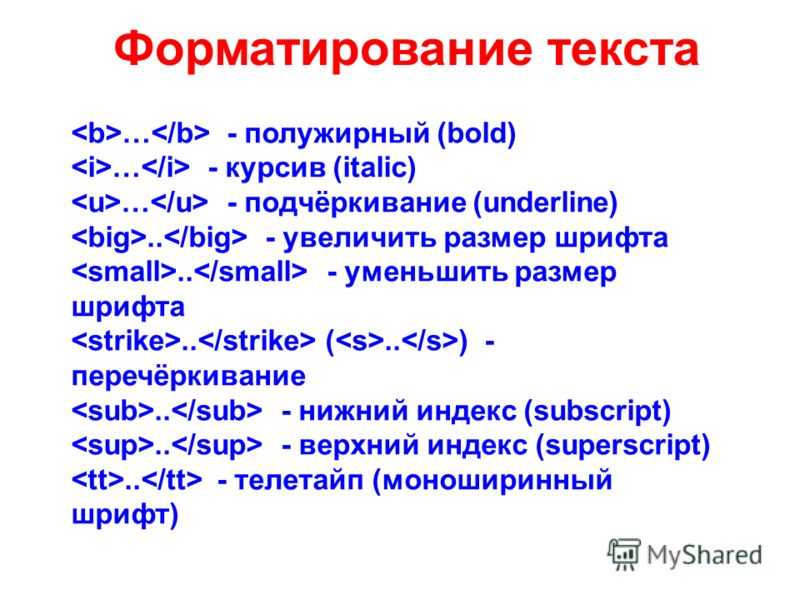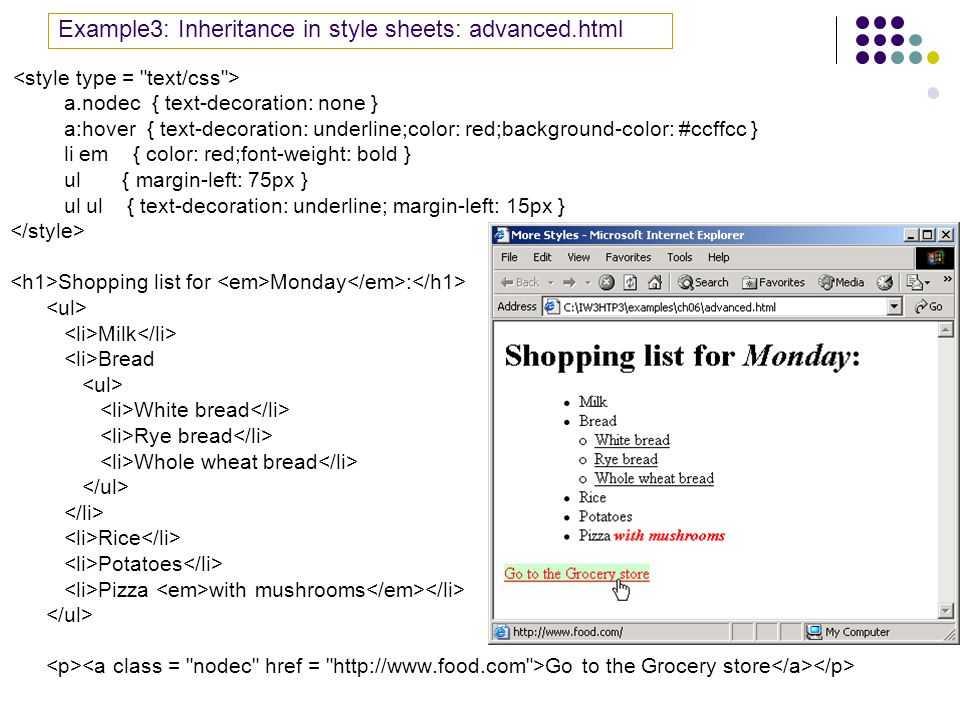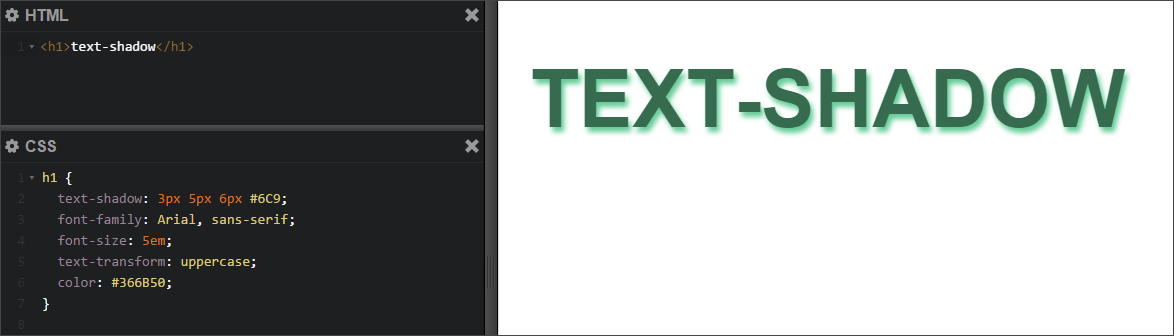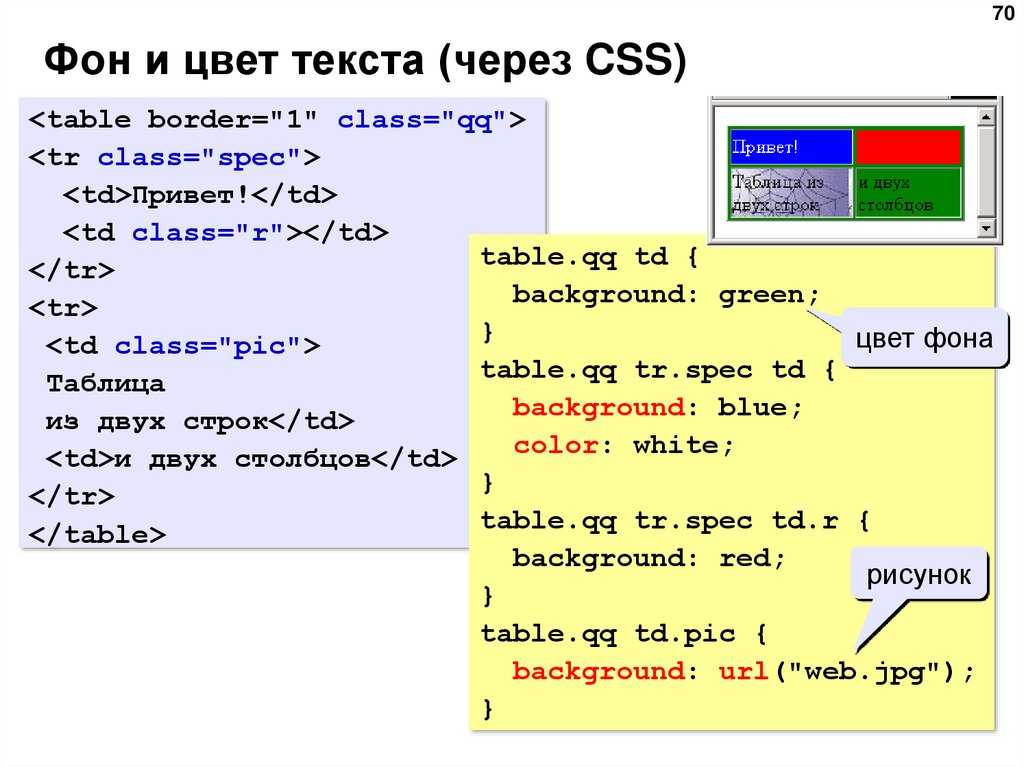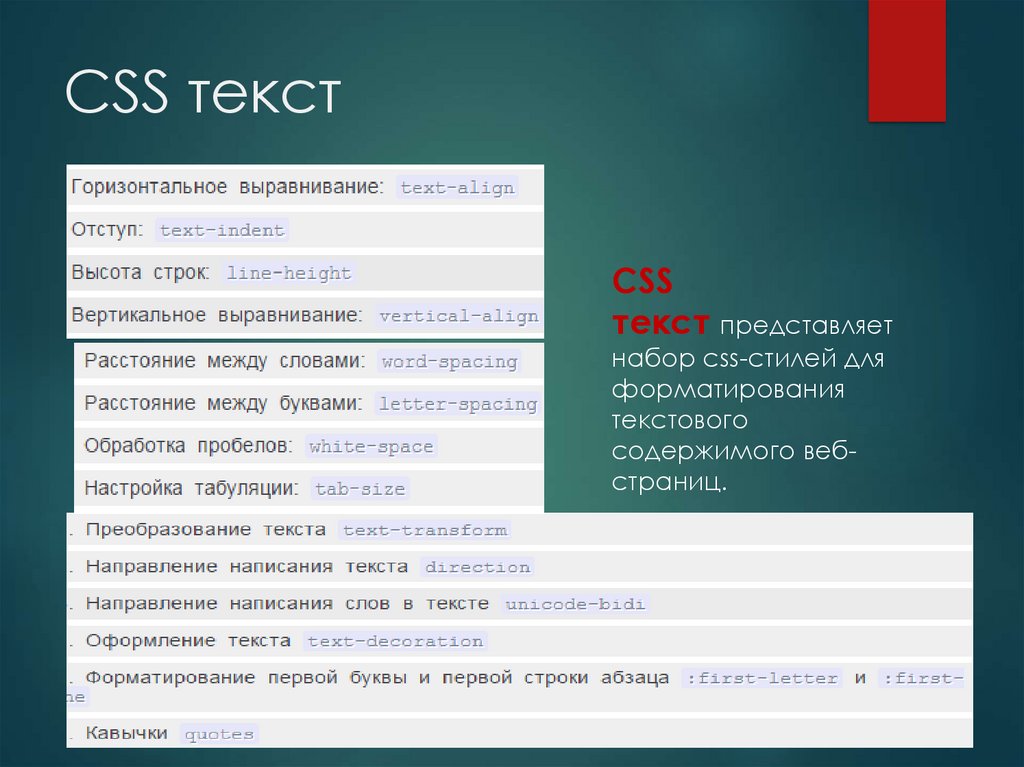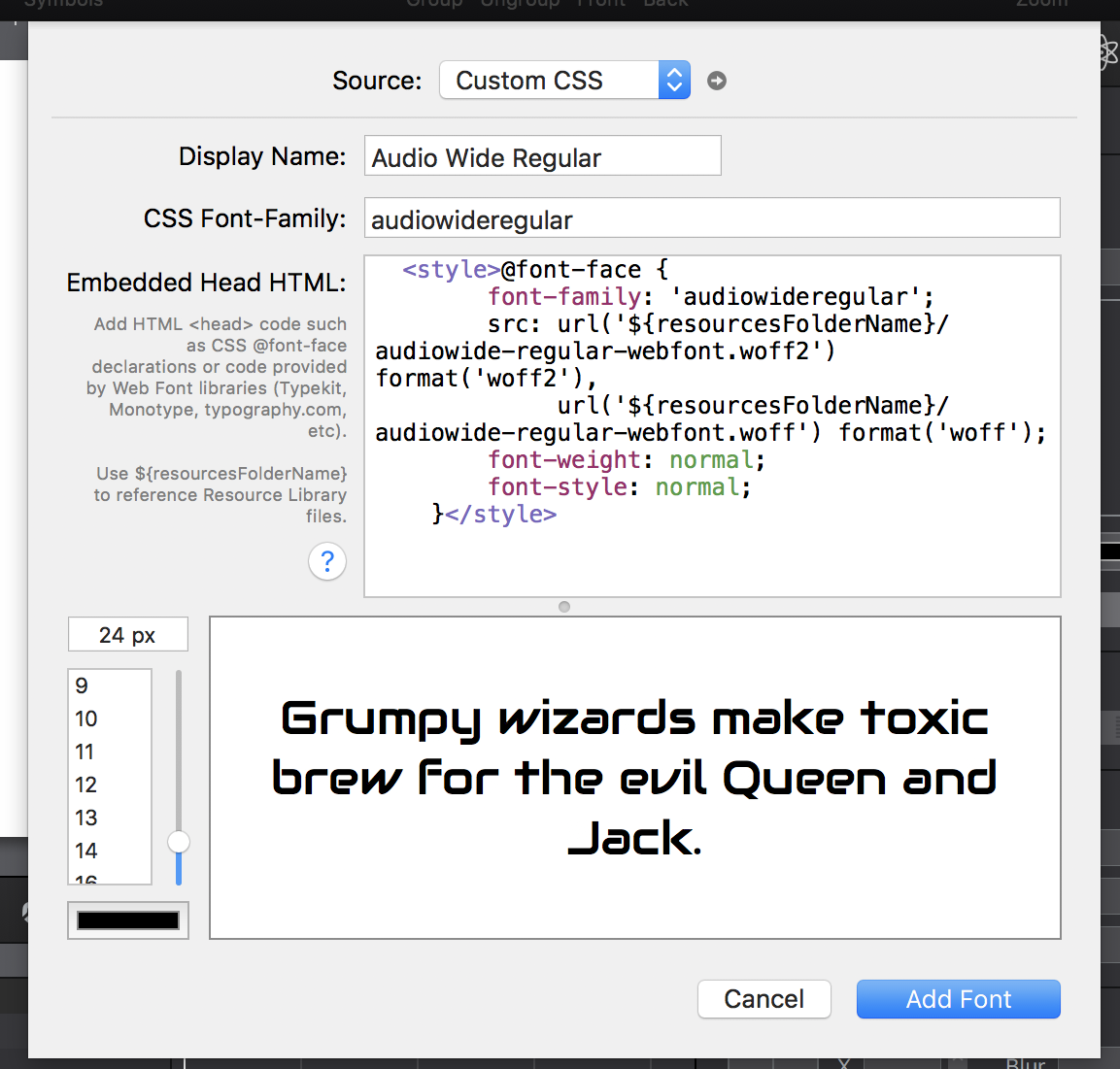
Форматирование текста — средства его изменения, такие как выбор начертания шрифта и использование эффектов, позволяющих менять вид текста. В табл. 1 перечислены основные теги, которые применяются для изменения оформления текста.
| Код HTML | Описание | Пример |
|---|---|---|
| <b>Текст</b> | Жирное начертание текста | Текст |
| <i>Текст</i> | Курсивное начертание текста | Текст |
| <sup>Текст</sup> | Верхний индекс | e=mc2 |
| <sub>Текст</sub> | Нижний индекс | H2O |
| <pre>Текст</pre> | Текст пишется как есть, включая все пробелы | Текст |
| <em>Текст</em> | Курсивный текст | Текст |
| <strong>Текст</strong> | Жирное начертание текста | Текст |
Любые теги форматирования текста можно использовать совместно друг
с другом.
Чтобы сделать текст одновременно жирным и курсивным шрифтом
используется сочетание тегов <b> и <i>
(пример 1). Их порядок в данном случае не важен.
Пример 1. Жирный курсивный текст
<!DOCTYPE HTML PUBLIC "-//W3C//DTD HTML 4.01//EN" "http://www.w3.org/TR/html4/strict.dtd"> <html> <head> <meta http-equiv="Content-Type" content="text/html; charset=utf-8"> <title>Текст</title> </head> <body> <p>Он словно вырезан из <b>камня</b>, стоек и неподвижен в отличие от его противников. <i>Дух и жизненная сила</i> в нём достигла <b><i>совершенства</i></b>. Но вот беда — никто не смеет принять его вызов.</p> </body> </html>
Результат данного примера показан на рис. 1.
Рис. 1. Вид курсивного жирного начертания текста
Использование тегов <sup> и <sub>
сдвигает текст относительно базовой линии и уменьшает размер шрифта (пример 2).
Пример 2. Создание нижнего индекса
<!DOCTYPE HTML PUBLIC "-//W3C//DTD HTML 4.01//EN" "http://www.w3.org/TR/html4/strict.dtd"> <html> <head> <meta http-equiv="Content-Type" content="text/html; charset=utf-8"> <title>Текст</title> </head> <body> <p><b>Формула изумруда:</b> <i>Be<sub>3</sub>Al<sub>2</sub>(SiO<sub>3</sub>)<sub>6</sub></i></p> </body> </html>
Результат данного примера показан на рис. 2.
Рис. 2. Нижний индекс в тексте
Теги <strong> и <em> выполняют те же функции, что теги <b> и <i>, но написание последних короче, привычней и удобней.
Следует отметить, что теги <b> и <strong>, также
как <i> и <em> являются не совсем эквивалентными
и заменяемыми. Первый тег <b> — является тегом физической
разметки и устанавливает жирный текст, а тег <strong> —
Текстовый эффект немого кино
Текстовый эффект немого кино — классический эффект в стиле ретро. Как следует из названия, у вас есть эффект старой текстовой карты фильма с дрожащей пленкой и линиями. Если вы разрабатываете развлекательный веб-сайт, вы можете использовать этот эффект, чтобы выделить важный контент. Еще одна хорошая вещь в этом эффекте — создатель сделал это исключительно с использованием HTML5 и CSS3.